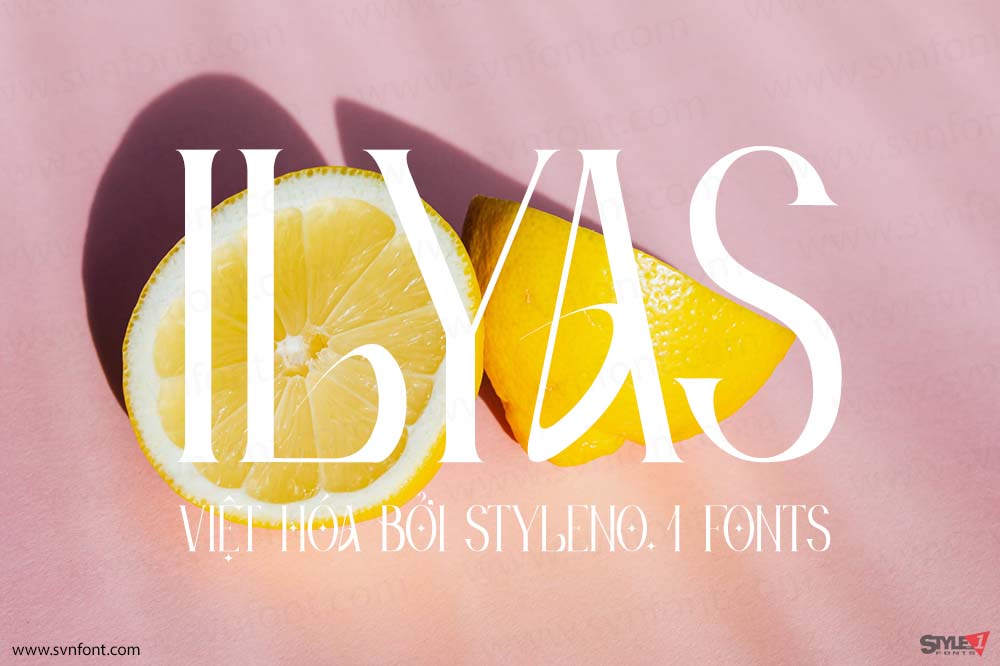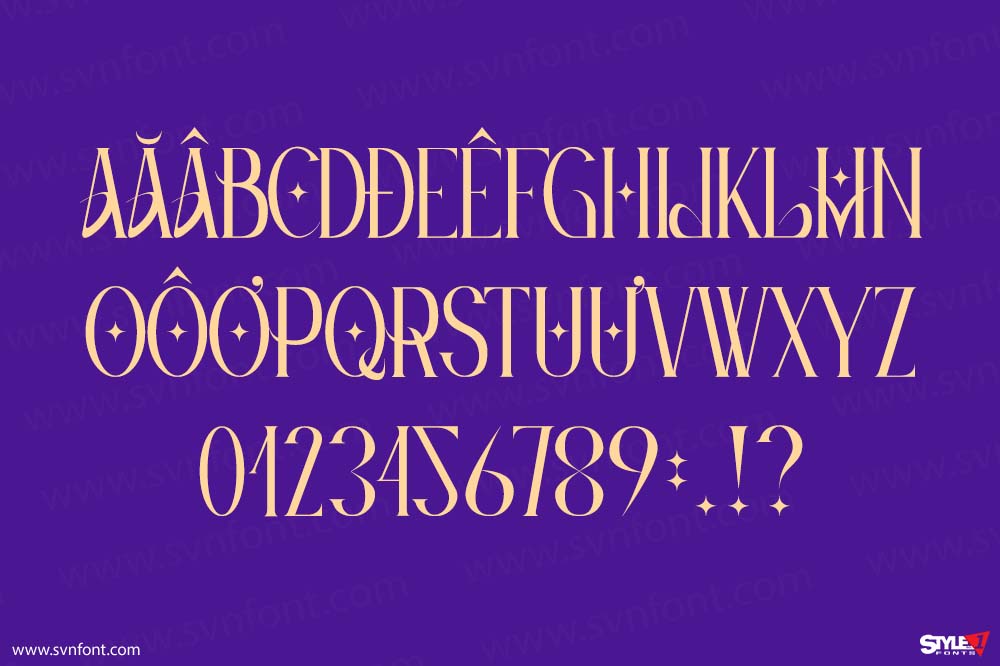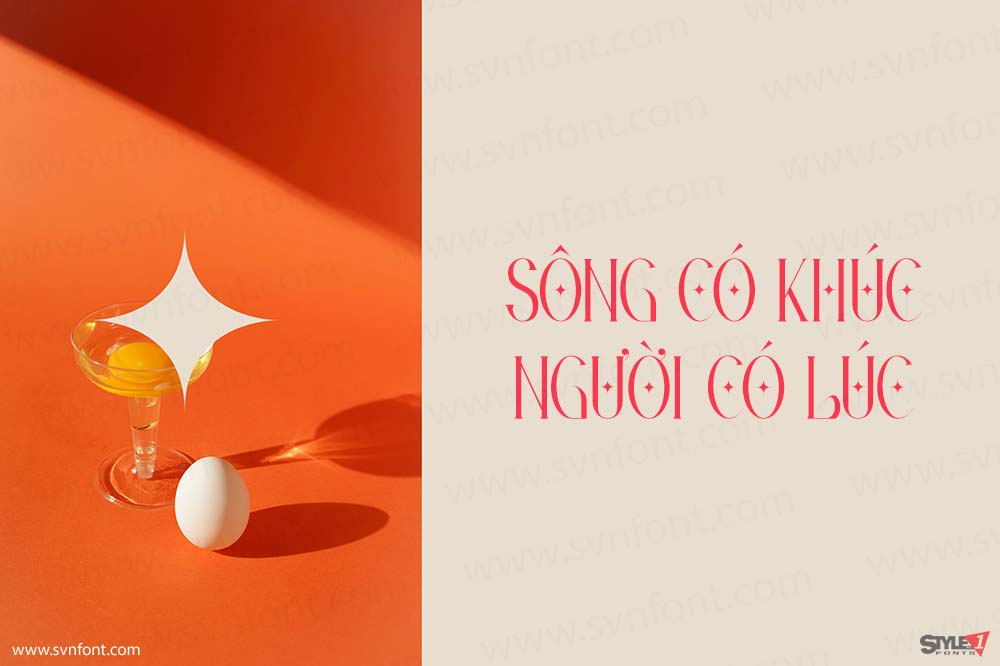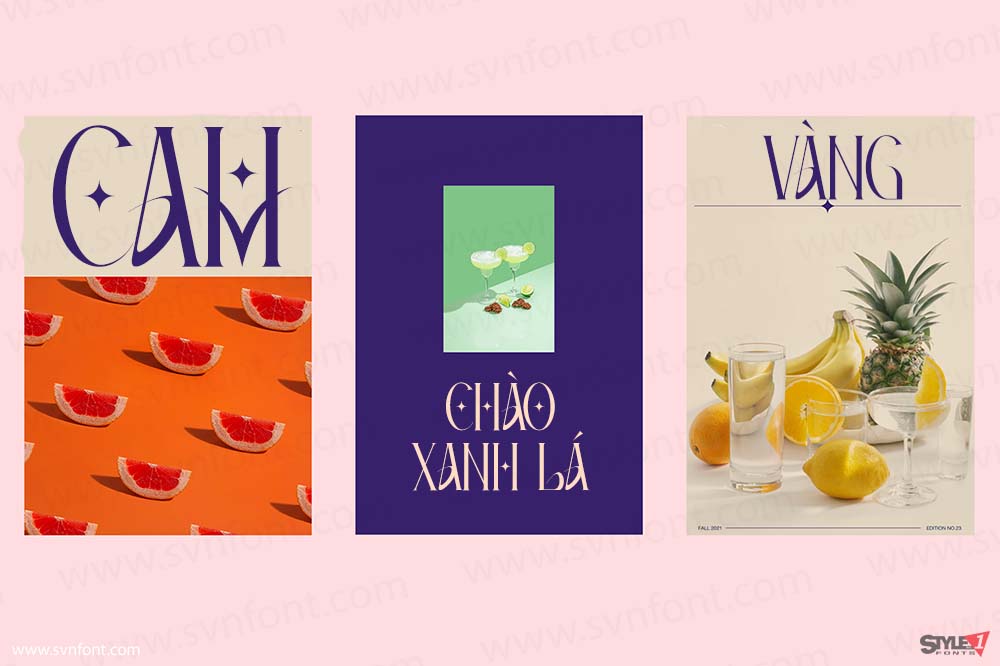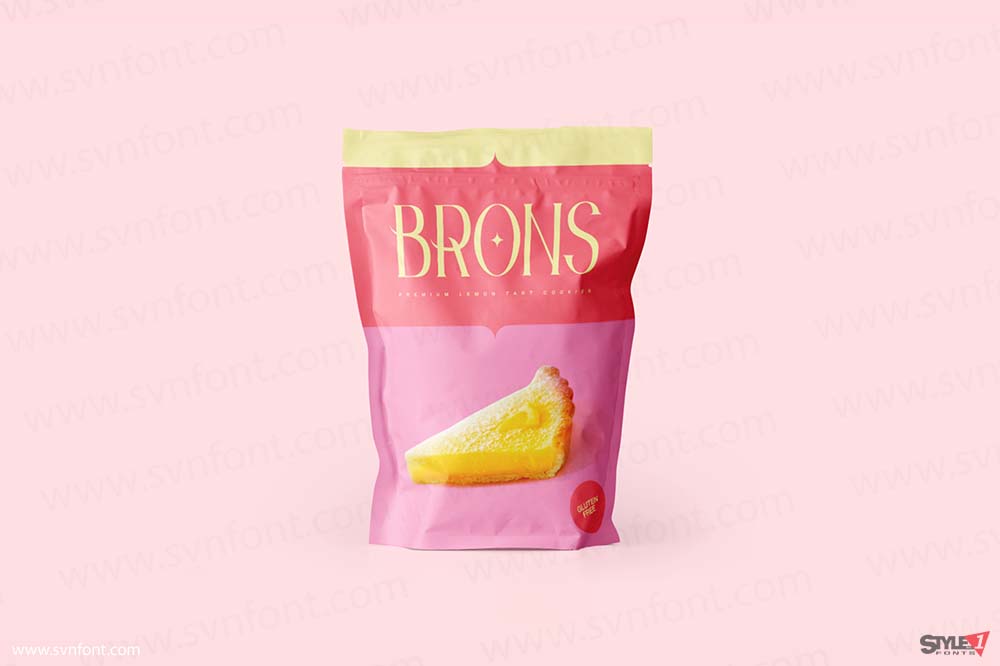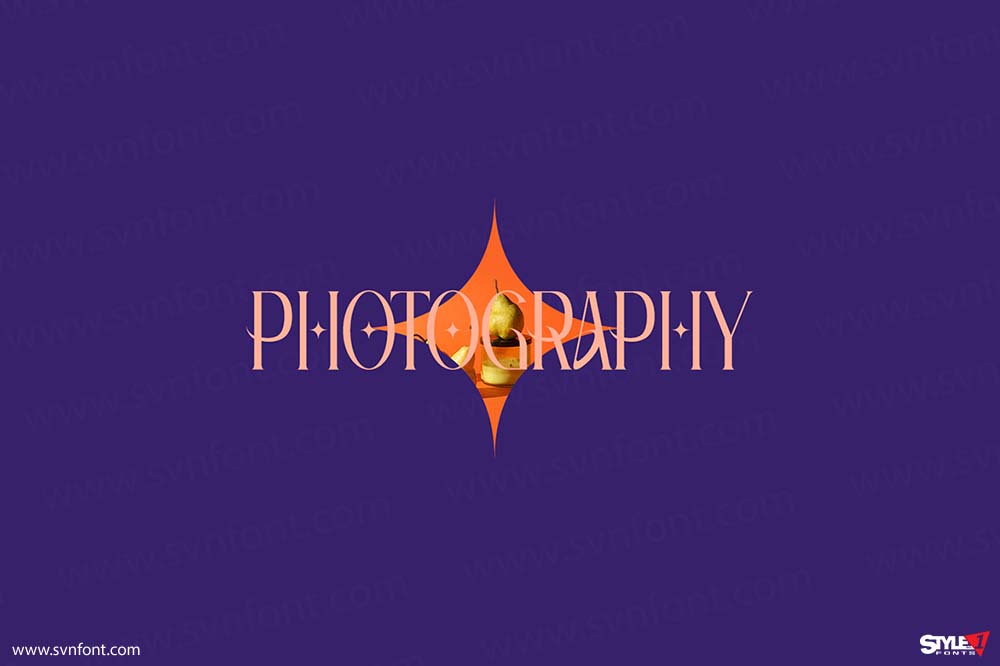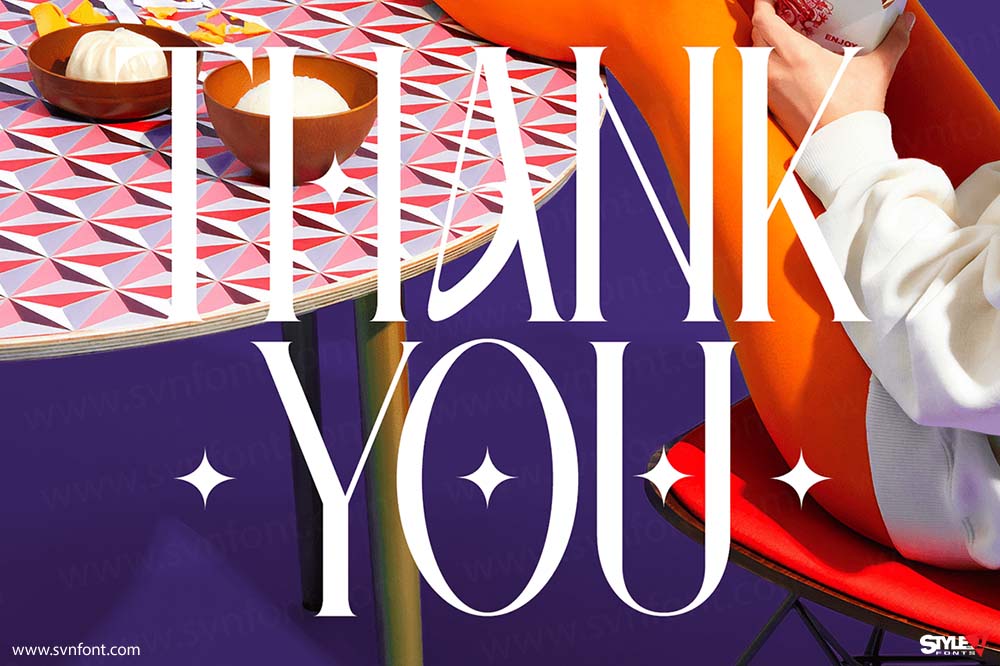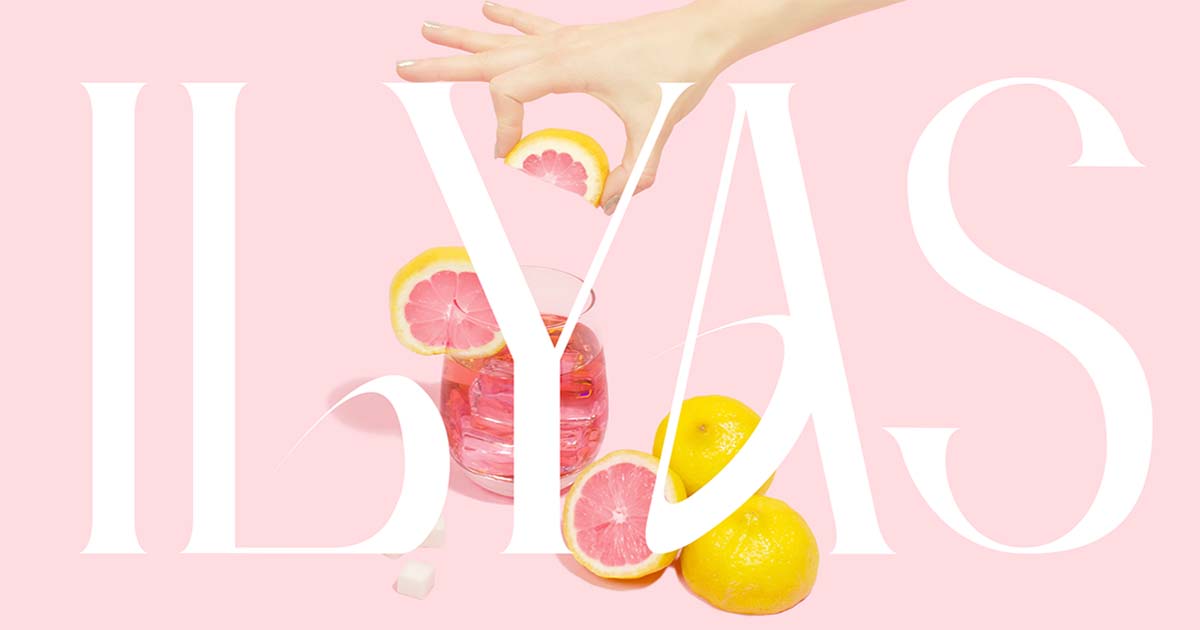
Font Việt Hóa - Ilyas Font Trang Trí Mang Phong Cách Hiện Đại
Ilyas là phông chữ hiển thị serif miễn phí lấy cảm hứng từ các yếu tố trang trí mạnh mẽ. Với các đường nét sắc nét và phong cách cô đọng, nó hoàn hảo cho các tiêu đề lớn hoặc được sử dụng như một phần tử đồ họa riêng biệt.